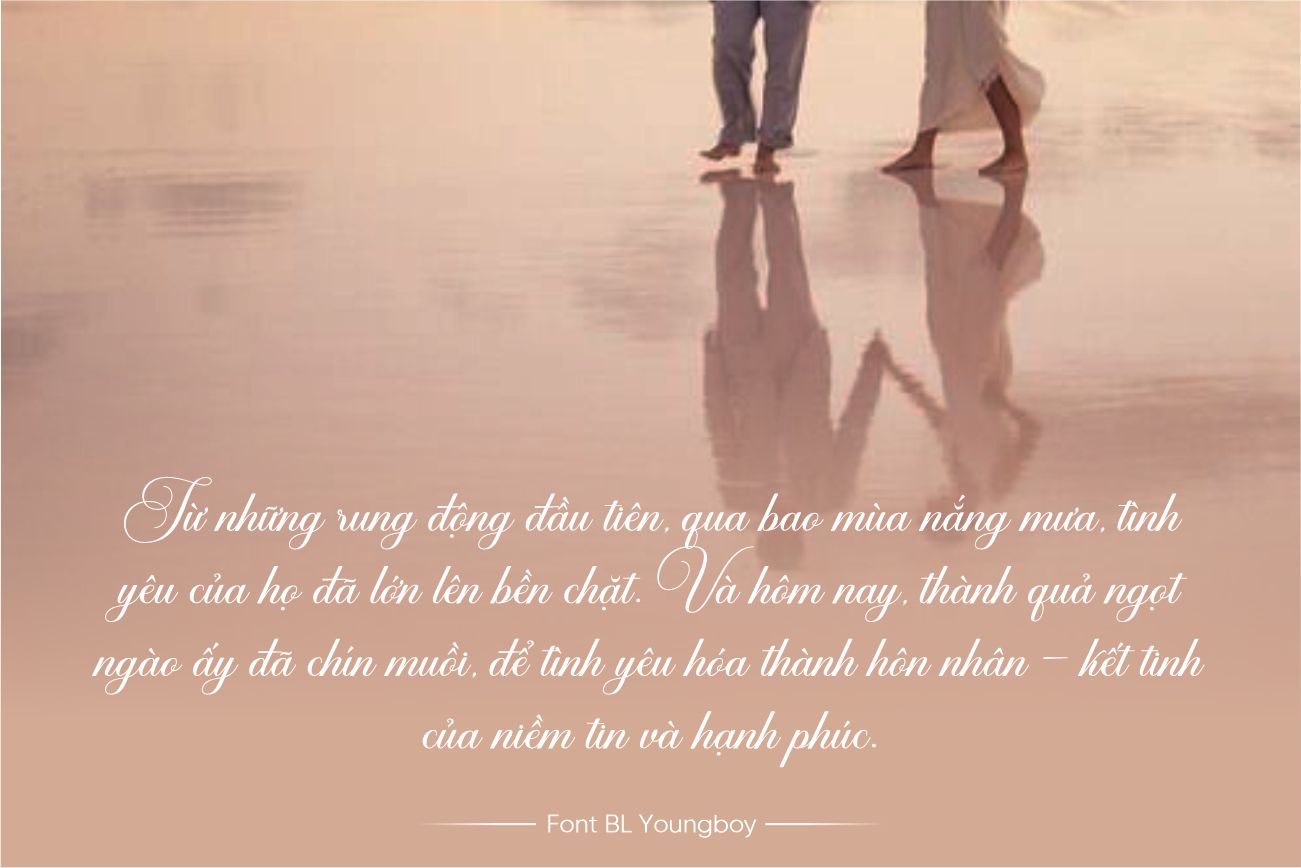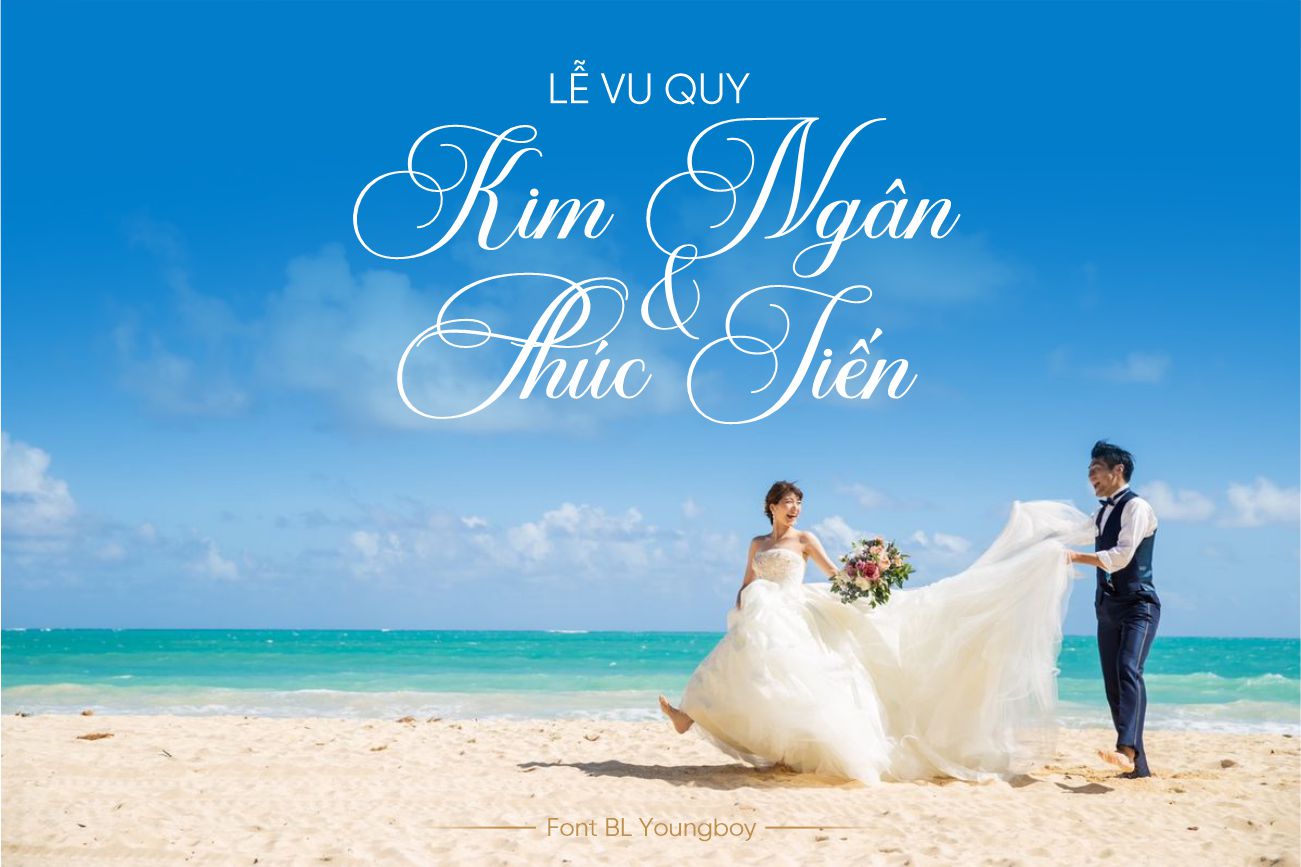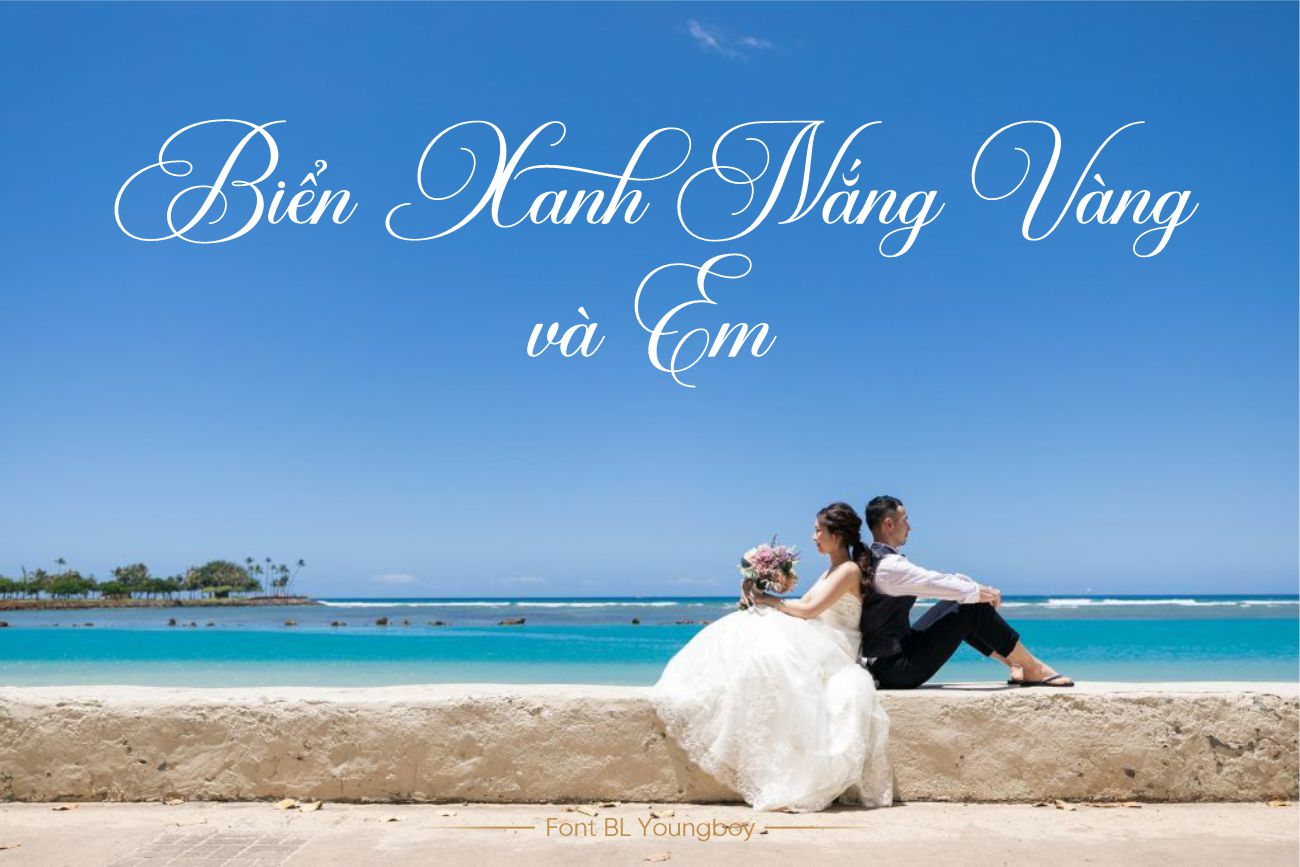
Font chữ Script cho thiệp cưới - BL Youngboy Việt hóa
Trong thế giới thiết kế, những font chữ viết tay nghệ thuật luôn được săn đón nhờ khả năng truyền tải cảm xúc tinh tế và mang lại dấu ấn cá nhân đặc biệt. Giữa vô số lựa chọn, font chữ BL Youngboy Việt hóa nổi bật như một làn gió mới: mềm mại, lãng mạn nhưng cũng vô cùng ứng dụng. Nếu bạn đang tìm kiếm một font chữ script lãng mạn để sử dụng cho thiệp cưới, typography nghệ thuật hay các dự án thiết kế thương hiệu, thì BL Youngboy chính là gợi ý lý tưởng.
Font chữ BL Youngboy là gì?
BL Youngboy là một kiểu font script mang phong cách viết tay tự nhiên, uyển chuyển và đầy cảm xúc. Font được thiết kế nhằm tạo sự gắn kết giữa sự lãng mạn cổ điển và tính hiện đại trong thiết kế, nhờ đó dễ dàng ứng dụng cho nhiều loại ấn phẩm khác nhau.
Nguồn gốc và tác giả gốc của font chữ Youngboy
Youngboy vốn là sản phẩm của một nhà thiết kế quốc tế, hướng đến sự sang trọng trong các thiết kế thiệp, branding và typography nghệ thuật. Với đường nét bay bổng và chi tiết ligatures tinh tế, font mang lại cảm giác mềm mại, rất phù hợp với các thiết kế liên quan đến tình yêu và sự gắn kết.
Quá trình Việt hóa bởi Team BL
Phiên bản BL Youngboy Việt hóa được thực hiện bởi Team BL, nhóm thiết kế font chữ nổi tiếng tại Việt Nam. Quá trình Việt hóa đã được tối ưu hóa toàn bộ hệ thống dấu tiếng Việt, chỉnh sửa kerning để font hiển thị hoàn hảo, từ đó giúp designer Việt có thể ứng dụng trực tiếp mà không lo bị lỗi ký tự.
Đặc điểm nổi bật của font chữ BL Youngboy
Phong cách viết tay nghệ thuật với đường nét uyển chuyển
BL Youngboy mang phong cách font chữ viết tay nghệ thuật, với những đường nét thanh mảnh, uốn lượn tinh tế. Các ký tự liền mạch giúp dòng chữ trông mềm mại và tự nhiên, tạo cảm giác như được viết bằng bút lông hoặc bút mực cao cấp.
Sự lãng mạn của font chữ script trong thiết kế hiện đại
Không chỉ đẹp mắt, BL Youngboy còn gợi lên sự lãng mạn – yếu tố rất cần thiết cho các thiết kế mang tính cảm xúc. Chính vì vậy, font này thường được chọn làm font chữ script lãng mạn trong thiệp cưới, thiệp mời sự kiện hoặc poster mang hơi hướng tình yêu.
Hỗ trợ đầy đủ dấu tiếng Việt và tính ứng dụng cao
Phiên bản Việt hóa của BL Youngboy đã khắc phục hạn chế thường gặp ở các font script quốc tế: thiếu dấu tiếng Việt. Giờ đây, bạn có thể thoải mái sử dụng để thiết kế từ thiệp mời, slogan cho đến logo thương hiệu bằng tiếng Việt mà không gặp trở ngại nào.
Ứng dụng của font chữ BL Youngboy trong thiết kế
Font chữ đẹp cho thiệp cưới sang trọng
Một tấm thiệp cưới không chỉ là lời mời đơn thuần mà còn là dấu ấn tình yêu của đôi uyên ương. Font chữ đẹp cho thiệp cưới như BL Youngboy sẽ biến tấm thiệp trở nên sang trọng và tinh tế hơn bao giờ hết.
Font chữ viết thiệp mời & thiệp cưới cá nhân hóa
Mỗi cặp đôi đều muốn thiệp cưới của mình mang phong cách riêng. BL Youngboy với sự mềm mại và lãng mạn giúp cá nhân hóa thiệp cưới, thiệp mời sự kiện, tạo sự khác biệt độc đáo.
Dùng trong logo, poster và typography nghệ thuật
Không chỉ dừng lại ở thiệp mời, BL Youngboy còn thích hợp cho các dự án sáng tạo khác như logo thương hiệu cao cấp, poster quảng bá sự kiện, typography nghệ thuật hoặc các thiết kế trên mạng xã hội.